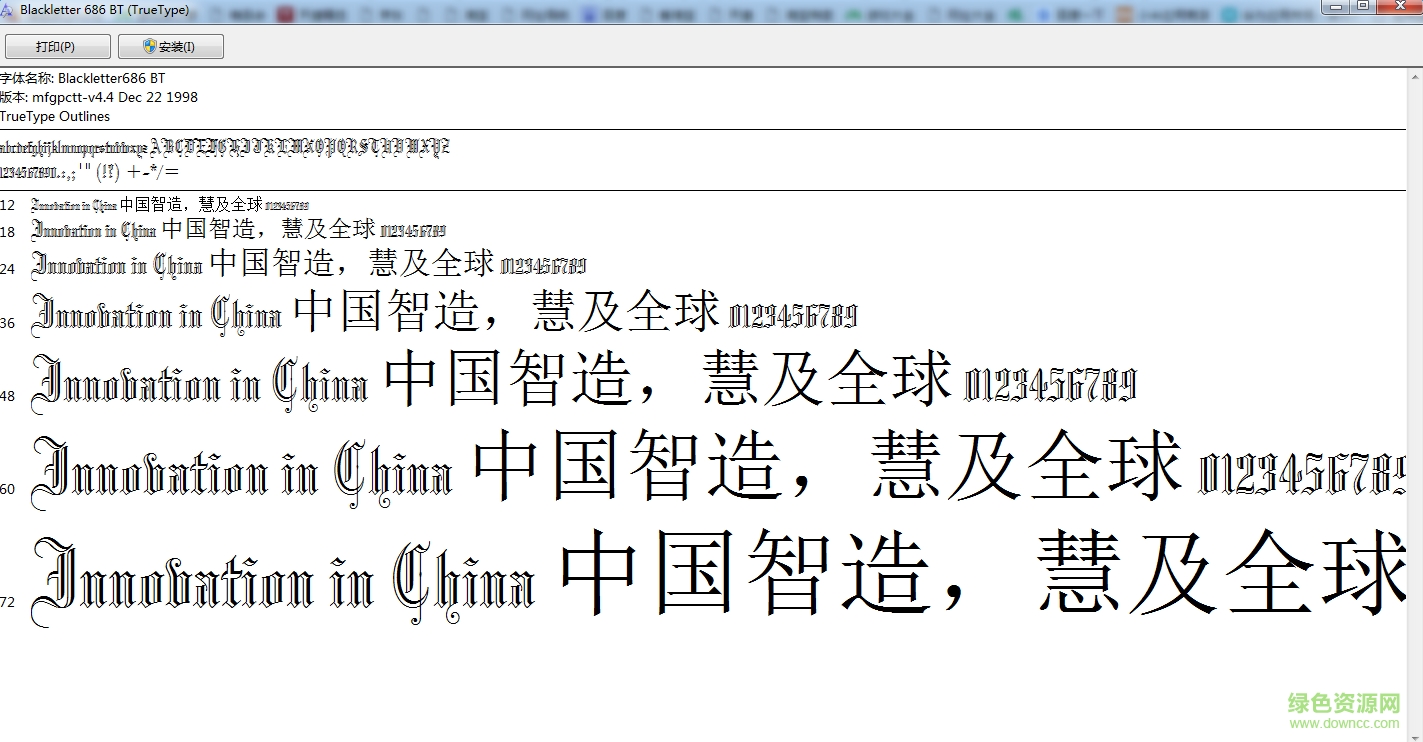
blackletter字體又叫哥特式字體,是一種經(jīng)典的英文字體,這款字體字型華麗,裝飾繁復(fù),帶有強(qiáng)烈的藝術(shù)風(fēng)格!常用于哥特設(shè)計(jì)方面,喜歡的朋友歡迎在綠色資源網(wǎng)下載!
“Blackletter” 也叫做哥特體,在公元1150年到17世紀(jì),它曾是風(fēng)靡歐洲的手寫體,直到20世紀(jì),這種字體也還被用于書寫德語。哥特這個(gè)名字最初是在15世紀(jì)文藝復(fù)興中期的意大利,被文藝復(fù)興人文學(xué)者認(rèn)為是野蠻的代表。哥特就是類似與沒有野蠻的,沒有文化的。